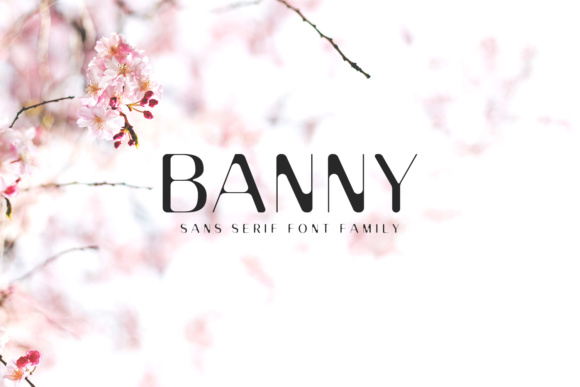
Banny Sans Serif Family
適切なデザイン要素を見つけるのは難しい場合がありますが、Banny Sans Serif Familyは作品を即座に引き立てる優れたコレクションを提供します。
POD(オンデマンド印刷)製品、結婚式の招待状、またはソーシャルメディアのグラフィックを作成している場合でも、Banny Sans Serif Familyは理想的です。